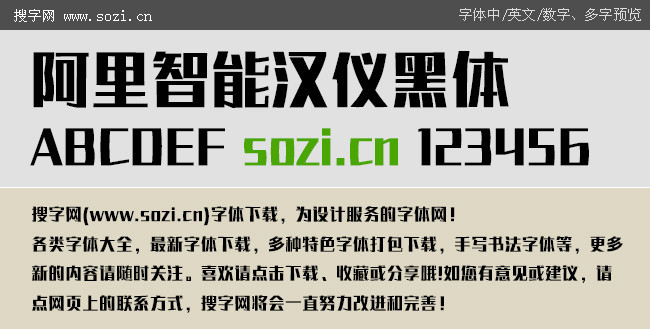
阿里智能漢儀黑體
搜字網提供一款阿里智能漢儀黑體字體下載,阿里智能漢儀黑體是一款漂亮的藝術黑體字體,是漢儀字庫聯手阿里巴巴打造的第一款AI字體產品,漢智能黑體基于黑體的橫豎基本特征,加大橫豎粗細比例,字面飽滿填充整個內框,讓字體更加醒目,視覺沖擊力極強,能夠很好的與用戶對話,非常適用于電商類廣告設計。【 阿里漢儀智能黑體將免費提供給阿里用戶在阿里平臺進行使用!】